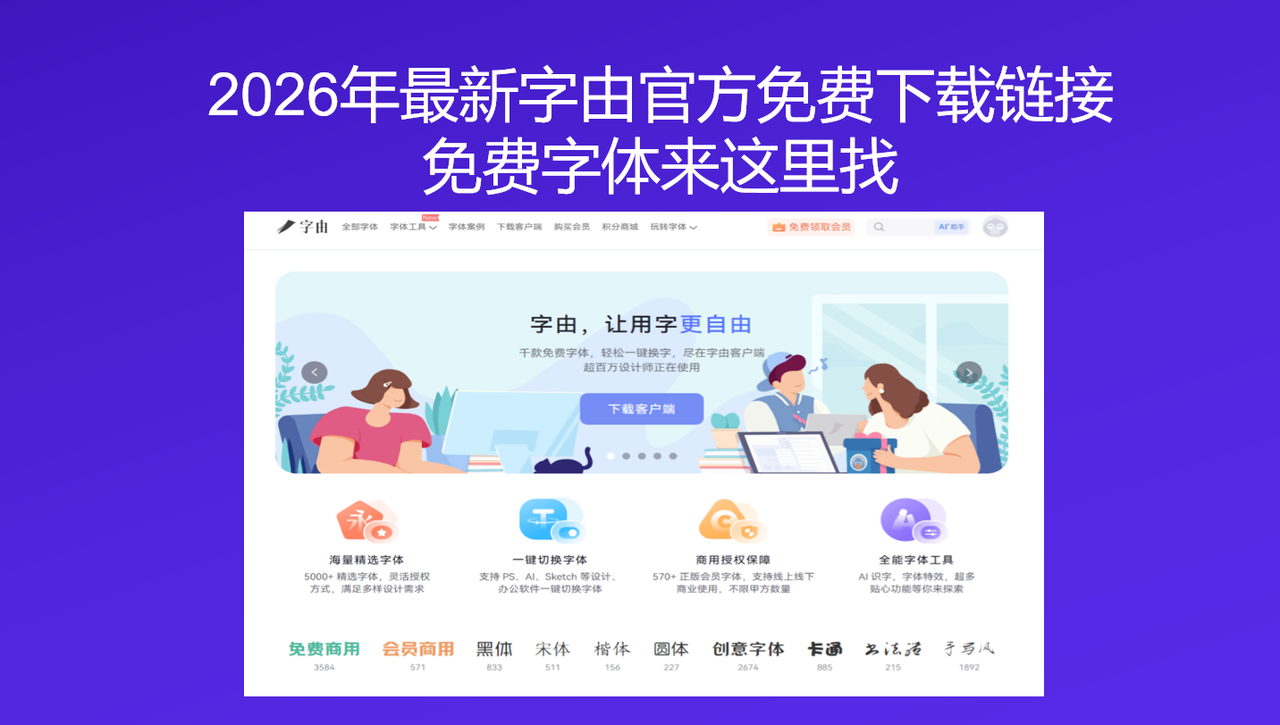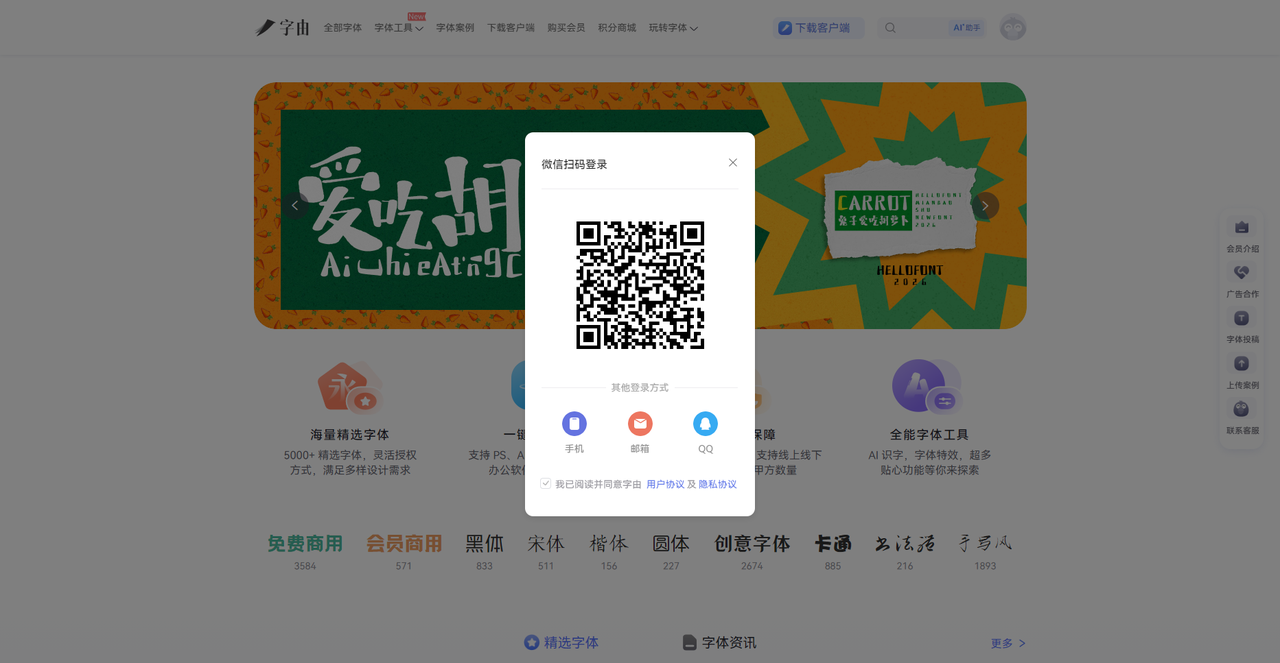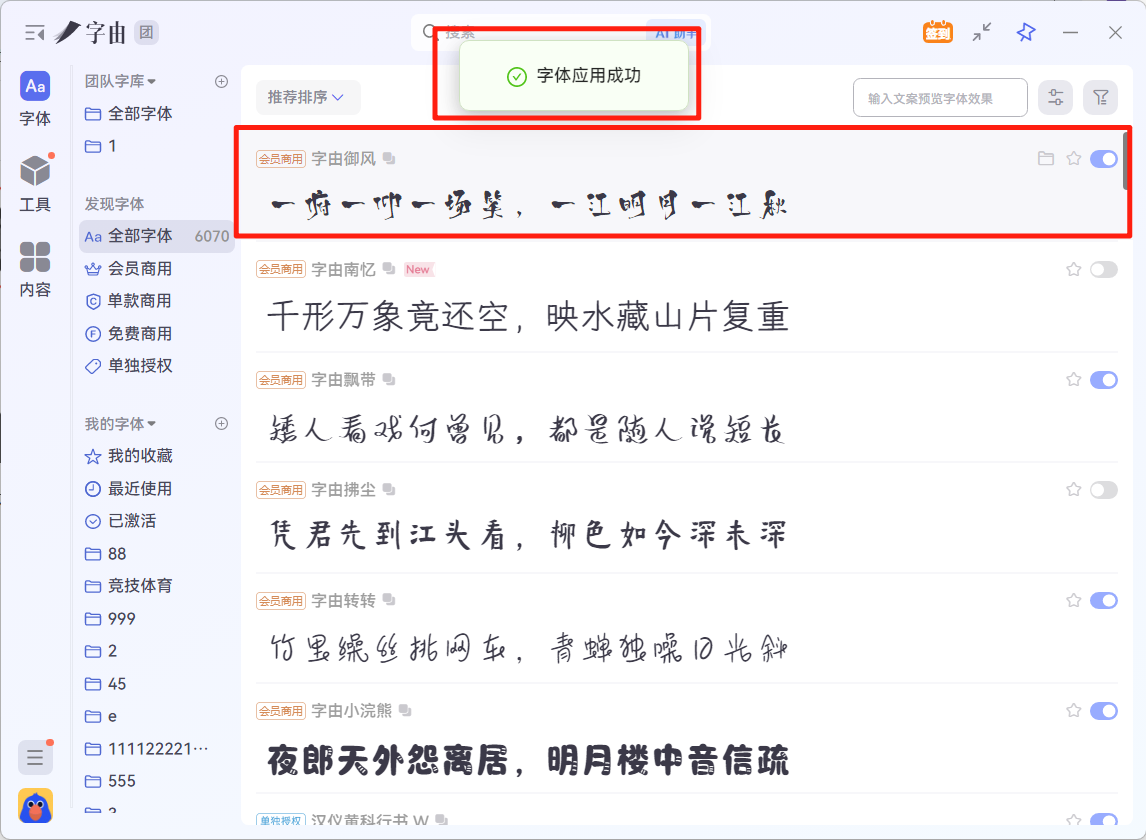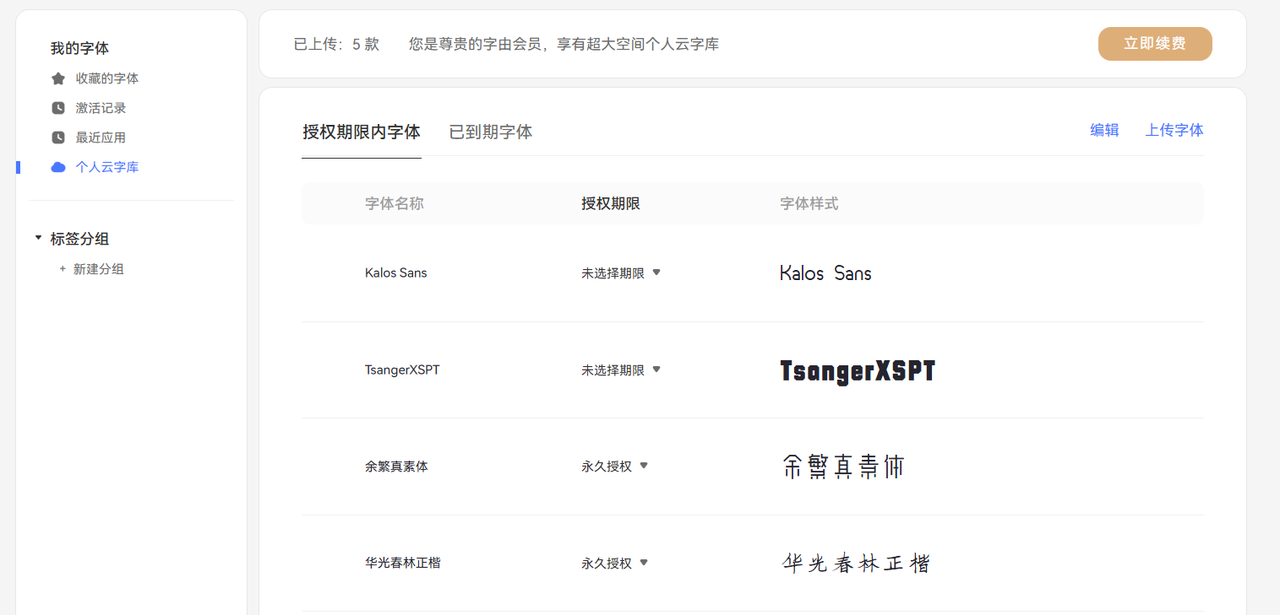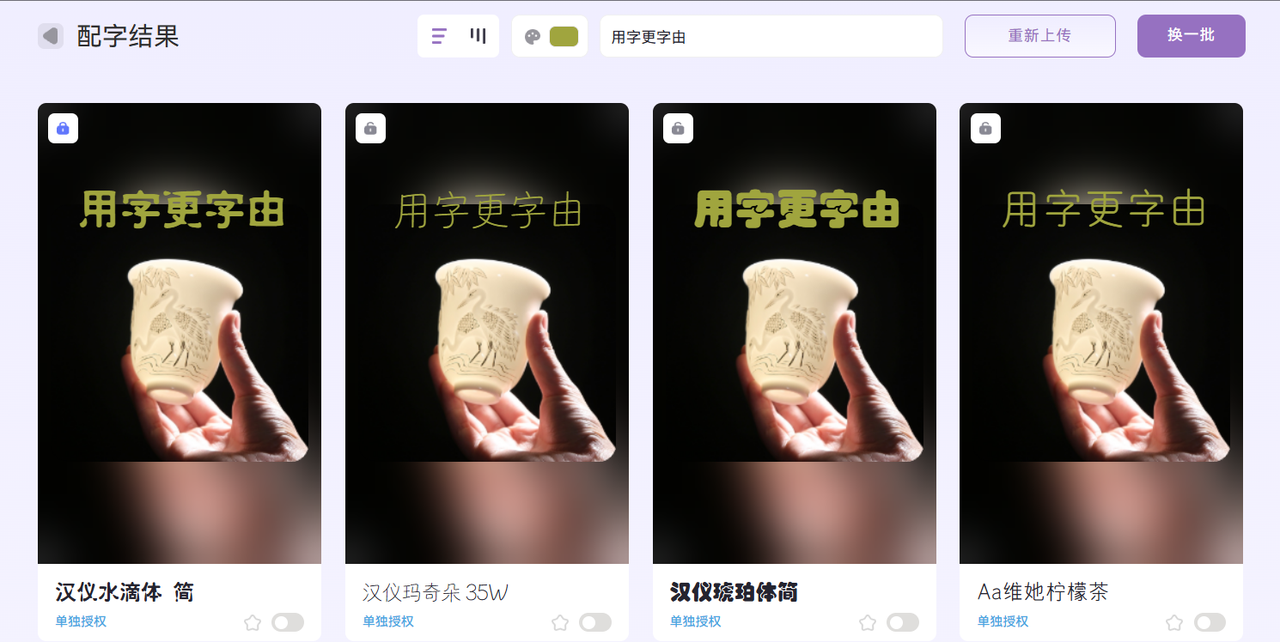
2026年最新字由官方免费下载链接,免费字体来这里找
做设计这么长时间,我总是被同行或者是阅读者们问这样一个问题:“你的字体都是从哪里下载的?”每次我都会告诉他们同一个答案:“我不是从哪里一款一款地下载的,而是直接用字由这个工具,打开客户端就有上万款字体,而且也不用到处找,并且还能一键替换字体到设计软件上。”到目前为止,字由的字体库已经更新到 10500 多款,免费商用字体也增加到了 3584 款,用起来比之前更顺手了。那么今天这篇文章就是专门教你怎么从官网注册、下载字由的。想告别设计还要去各个网站到处跑着找字体的日子,直接收藏这篇就行了。
1、字由是什么?
先来介绍一下字由,字由隶属于上海驿创信息技术有限公司,自2015年品牌创立以来,一直致力于解决设计师群体的用字问题。品牌核心宣传就是“让用户用字更自由”。目前,字由聚集了超千万设计师、创意人才、运营管理人员、商务人士、在校学生等忠实粉丝,服务了全球用户——不论小白还是大神,字由都会一路相伴。
3、字由核心功能详解
完成字由下载并登录客户端以后你发现这不仅仅是一个字体库,更是一个丰富的字体工具箱。下面我会挨个介绍字由最实用的一些功能!
字体一键应用到设计软件
通过字由客户端可实现在PS、AI、ID、XD、Figma、Sketch、CDR等设计软件中一键应用字体,无需下载,安装字体包,即可完成字体应用,省去了字体查找,下载,安装的麻烦,一键应用操作步骤。
打开设计软件(比如PS),新建一个文件,用文字工具输入一段文字,选中这个文字图层。
然后在字由客户端激活所需要使用的字体,然后你就可以看到你选择的字体成功替换到设计软件上了!是不是非常便捷?当你纠结于选哪款字体时,这个功能尤其好用:点一下换一款,哪款合适一眼就能看出来,试一款字体只要1秒钟。这才是真正的“用字自由”。
10500+海量字体库,3584 款免费商用
字由目前收录了 10500多款 精选字体,涵盖黑体、宋体、书法体、手写体、艺术体、Sans Serif、Serif 等各种风格。更重要的是,其中 3584款 是免费可商用的,你可以放心用在商业项目中,不用担心版权问题。同时你也不用担心字体多而导致眼花缭乱不知道选哪些,在点击全部字体后你可以看到有细分的筛选栏:
我还可以为大家推荐一些我常用的字体:
• 阿里妈妈东方大楷:大气稳重的楷书,适合传统文化设计
• 优设好身体:字形方正饱满,适合画册、公众号配文
• 思源黑体 Medium:经典开源字体,适合正文排版
个人云字库
以前我都是把字体包存在U盘里,但U盘容易丢,电脑也可能会坏。有了字由的个人云字库功能,这些问题都解决了。用户可上传本地字体至字由个人云字库,上传后字体可云端保存,并支持一键激活,换设备登录自动同步,极大方便多设备办公用户进行字体数据协同。
AI 智能工具辅助
字由还内置了多个AI工具,帮助设计师解决日常难题。
• AI识字:截图上传,AI就能识别出字体名称和授权类型。
• AI擦除:做海报时想去掉图片上的文字,又不想进PS慢慢修?上传图片,AI智能擦除后背景自动修复,完全看不出痕迹。
• AI配字:做海报不知道用什么字体合适?上传图片,AI自动识别图中的元素(风景、人物还是产品),从海量字体库中推荐最适合这款图片的字体。对新手特别友好,也能给老设计师带来新灵感。